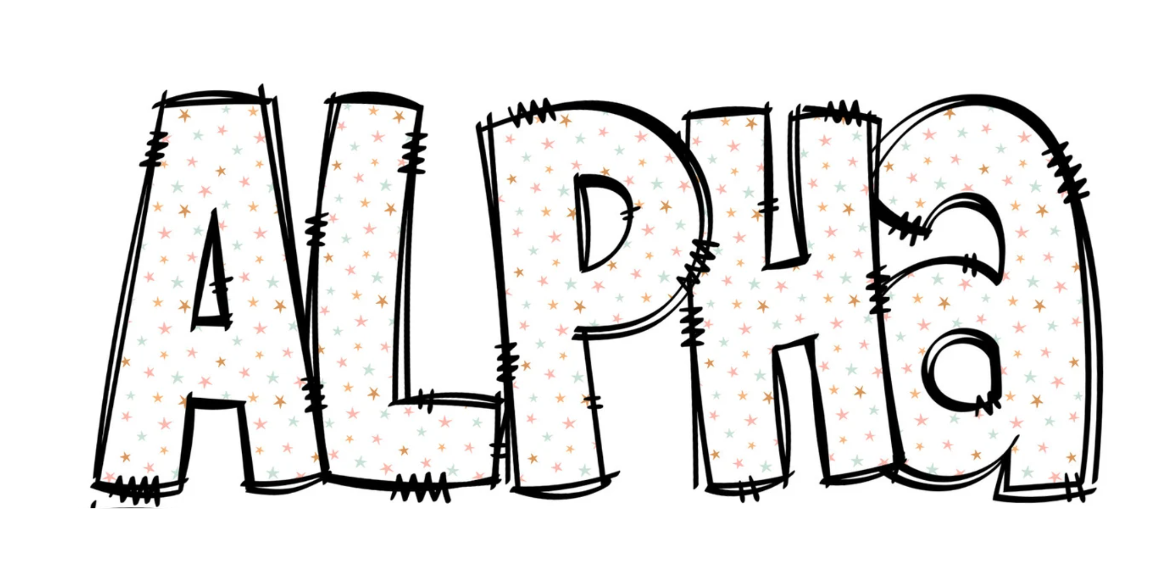
Menna Me font eka hoyala dennako
dilann Well-known member Jul 6, 2018 69,660 170,515 113 එකමත් එක රටක Mar 18, 2023 #3 custom font එකක් වෙන්න ඇති.. Reactions: avjayarathne and TechnWeb
L lasankandy Well-known member Jul 18, 2009 32,780 34,257 113 KY Mar 18, 2023 #6 www.myfonts.com ඔකට දාල බලන්න
TechnWeb Well-known member Dec 28, 2011 7,598 5,687 113 Mar 18, 2023 #8 illustrator walin trace karala balanna. oke fill eka nam amuthuwen dala wage. uda kiwa wage custom edapu ekakda danne ne
iSecure Junior member May 24, 2021 64 28 18 Mar 18, 2023 #9 lasankandy said: www.myfonts.com ඔකට දාල බලන්න Click to expand... awe nane TechnWeb said: illustrator walin trace karala balanna. oke fill eka nam amuthuwen dala wage. uda kiwa wage custom edapu ekakda danne ne Click to expand... na na meka font ekak. drawing karapu ekak nemai dilann said: custom font එකක් වෙන්න ඇති.. Click to expand... na machan Reactions: lasankandy
kinkon Well-known member Aug 5, 2007 116,187 2 116,552 113 Kandy ♕ පතිරූප දේස වාසෝ Mar 18, 2023 #11 Font Reactions: SupiriKollek